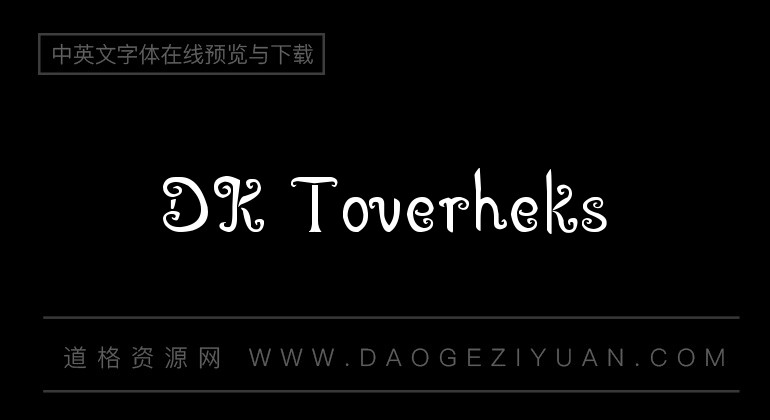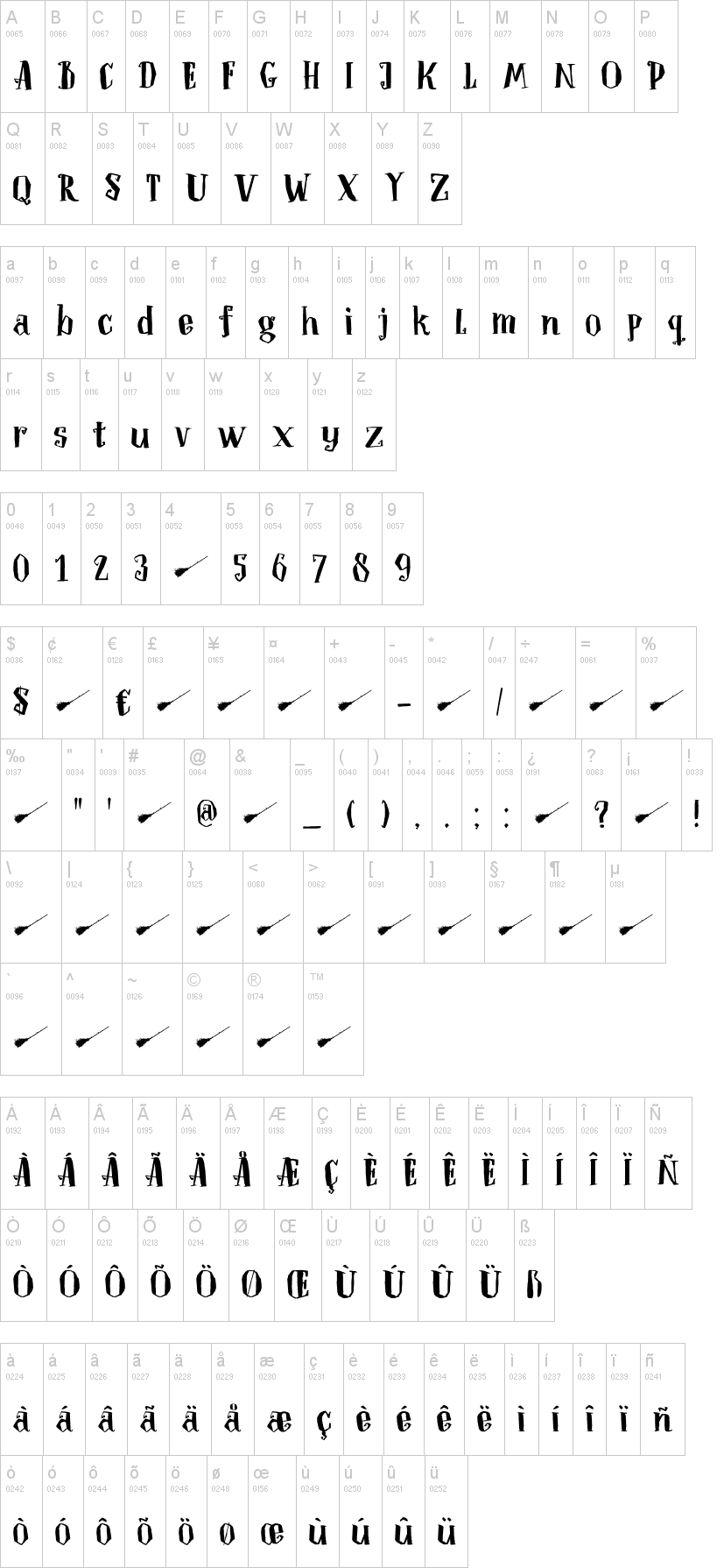
DK Toverheks 是一款具有古典风格的荷兰字体,由荷兰艺术家Dirk Koning创作。它拥有细节丰富的古典外观,并且具有强烈的古典气息。它的字母形状有着流畅的线条,而且字体的节奏也很好。它的设计简洁大方,可以用于各种类型的印刷,如书籍、杂志、海报等。它还可以用于网页设计,用于制作精美的网页标题、文字等。内容介绍
DK Toverheks是一款非常不错的手写艺术字体,具有很好的视觉感,适合于文化类的宣传设计、商业类品牌的广告和产品包装设计以及个性化文字排版等较多场景。